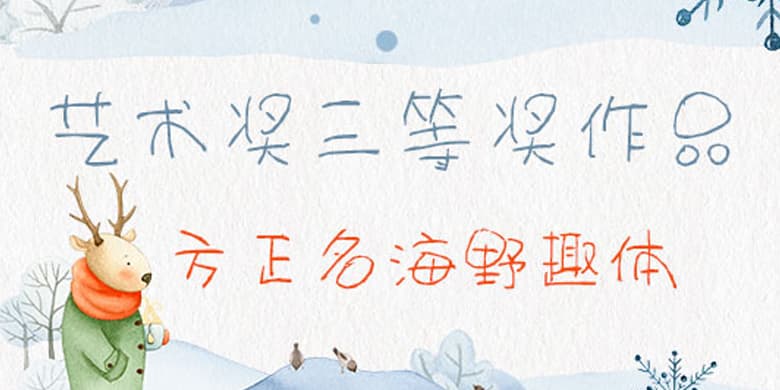
方正手迹-方正名海野趣体
品牌:方正手迹设计师:袁明海发行时间:2020字库编码:大陆简体(GB2312-80)分类:创意书写字体属性:精品字
方正名海野趣体,字体线条纤细略带弧度,字形部件天马行空,大小错落。好看的字体千篇一律,有趣的灵魂万里挑一,总之用上它你就是最特别的那一个。适用于少年儿童类的书刊、品牌广告和产品包装设计,综艺漫画用字,现代诗歌排版,以及社交网络的个性化用字。